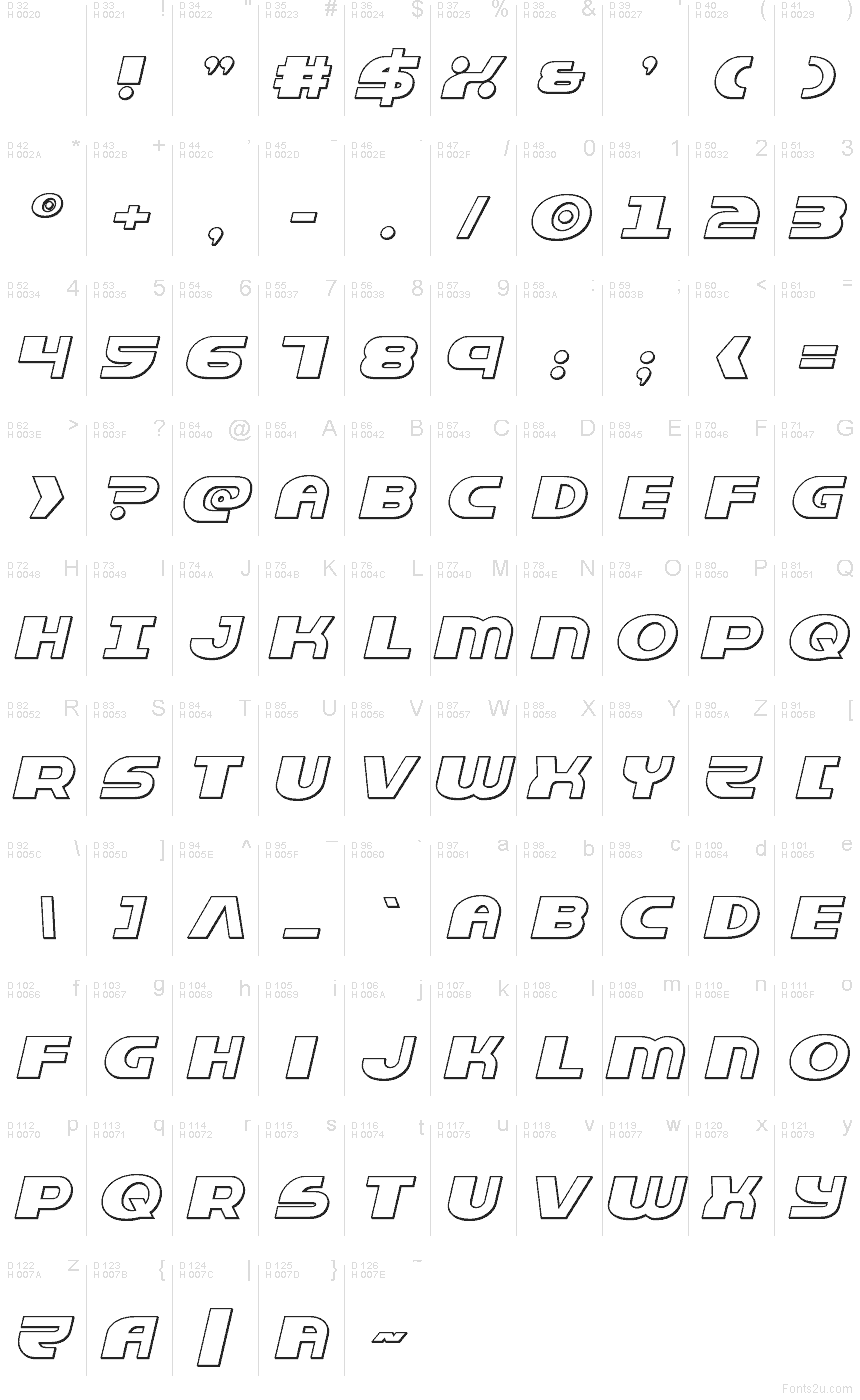
Dashiel 3D Italic de Iconian Fonts es una tipografía 3D de estilo display, gratuita y cursiva, con un aire deportivo retro-futurista. Sus mayúsculas se inclinan hacia adelante con formas anchas y sólidas, mientras que sus líneas de profundidad compensadas crean un borde tridimensional definido que recuerda más a los logotipos de arcade y al branding de ciencia ficción que a una tipografía sans serif inclinada convencional.
Encaja perfectamente en titulares de pósteres, títulos de juegos, portadas, conceptos de logotipos y tarjetas de presentación, donde su profundidad incorporada permite decir más con menos palabras. Al ser gratuita, es ideal para gráficos de streaming o maquetas de merchandising, especialmente cuando buscas que las letras tengan movimiento y volumen sin necesidad de añadir efectos extra.
Dashiel 3D Italic